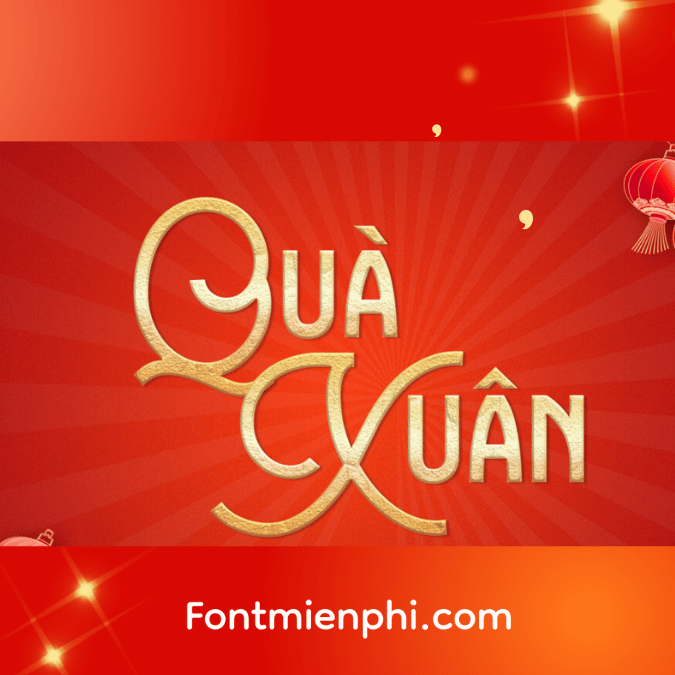
Font Việt hóa 1FTV VIP Colgneries ,Font tết
Font Việt hóa 1FTV VIP Colgneries
Font Việt hóa 1FTV VIP Colgneries là một trong những kiểu chữ được thiết kế đặc biệt để phục vụ nhu cầu sử dụng tiếng Việt trong các tài liệu, quảng cáo và thiết kế đồ họa. Font này không chỉ mang đến vẻ đẹp thẩm mỹ mà còn đảm bảo tính dễ đọc và khả năng sử dụng linh hoạt trong nhiều bối cảnh khác nhau.
Đặc điểm nổi bật Font Việt hóa 1FTV VIP Colgneries ,Font tết
1. Thiết kế hiện đại: Font 1FTV VIP Colgneries có thiết kế hiện đại, với các đường nét mềm mại và thanh thoát. Điều này giúp nó phù hợp với các sản phẩm sáng tạo, từ tờ rơi quảng cáo đến bìa sách hay các trang web.
2. Hỗ trợ đầy đủ các ký tự tiếng Việt: Font này được Việt hóa hoàn chỉnh, bao gồm tất cả các ký tự cần thiết cho việc viết tiếng Việt như dấu sắc, huyền, hỏi, ngã và nặng. Nhờ đó, người dùng có thể dễ dàng sử dụng font cho bất kỳ văn bản nào mà không gặp trở ngại về việc thiếu ký tự.
3. Dễ dàng phối hợp với các thành phần khác: Với phong cách thiết kế đơn giản nhưng tinh tế, 1FTV VIP Colgneries dễ dàng phối hợp với nhiều loại hình ảnh, màu sắc và kiểu dáng khác nhau, giúp tạo nên sự hài hòa trong các sản phẩm thiết kế.
4. Độ tương phản tốt: Kích thước chữ và độ dày đều được tính toán kỹ lưỡng, giúp cho văn bản dễ nhìn hơn trên nền màu sáng hoặc tối. Điều này rất quan trọng trong lĩnh vực quảng cáo và truyền thông, nơi mà sự thu hút ánh nhìn là rất cần thiết.
5. Ứng dụng đa dạng: Font có thể được sử dụng cho nhiều mục đích khác nhau như logo, tiêu đề, văn bản chính, hay thậm chí trong các ấn phẩm truyền thông xã hội. Điều này làm cho nó trở thành một lựa chọn linh hoạt cho các nhà thiết kế.
Kết luận
Tóm lại, font Việt hóa 1FTV VIP Colgneries không chỉ là một công cụ hữu ích cho việc viết tiếng Việt mà còn là một sản phẩm thiết kế đẹp mắt, giúp nâng cao giá trị thẩm mỹ cho bất kỳ tài liệu nào. Sự kết hợp giữa tính năng và thẩm mỹ khiến font này trở thành một lựa chọn tuyệt vời cho những ai đang tìm kiếm một kiểu chữ chất lượng cao để sử dụng trong công việc của mình.